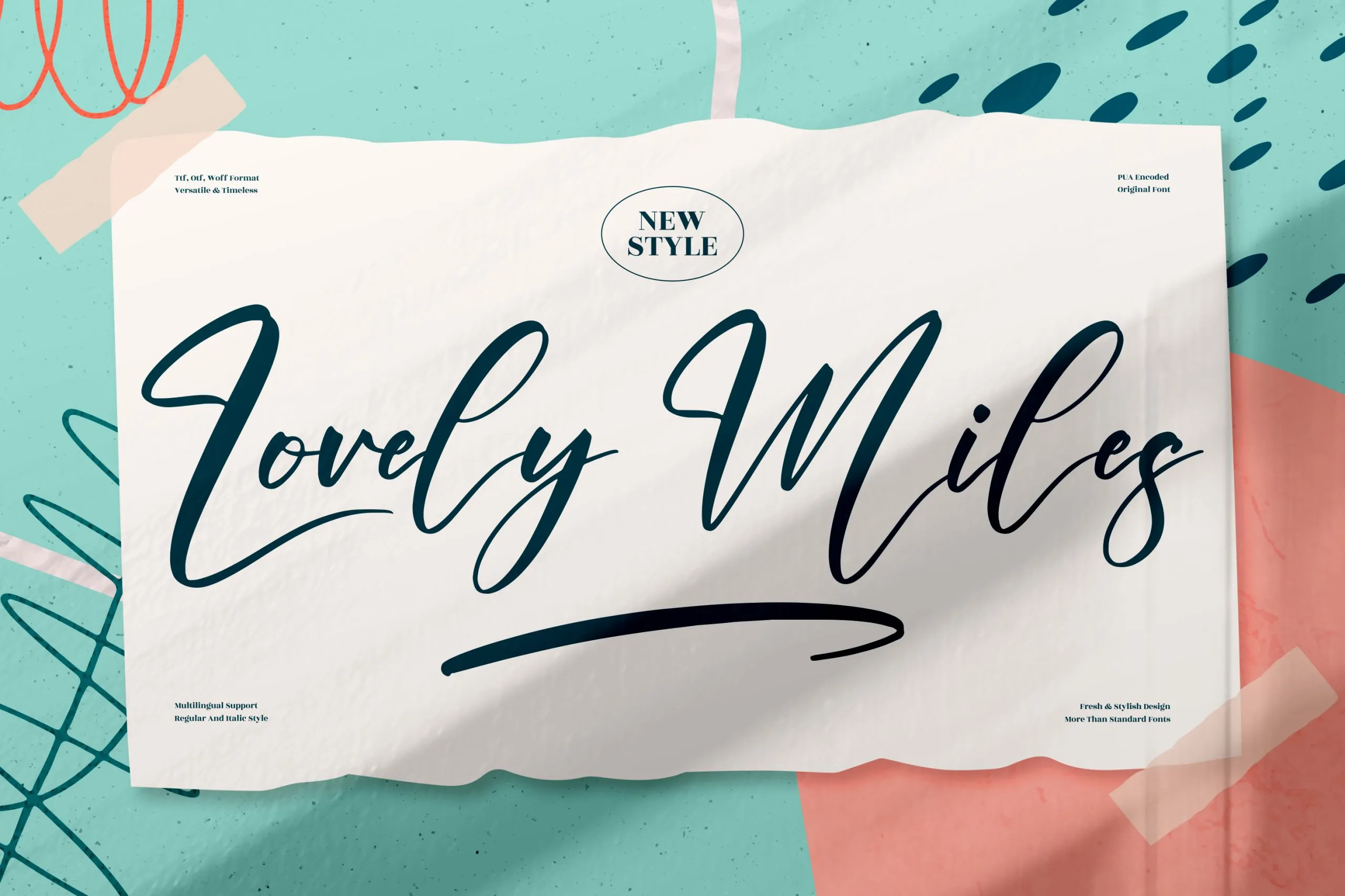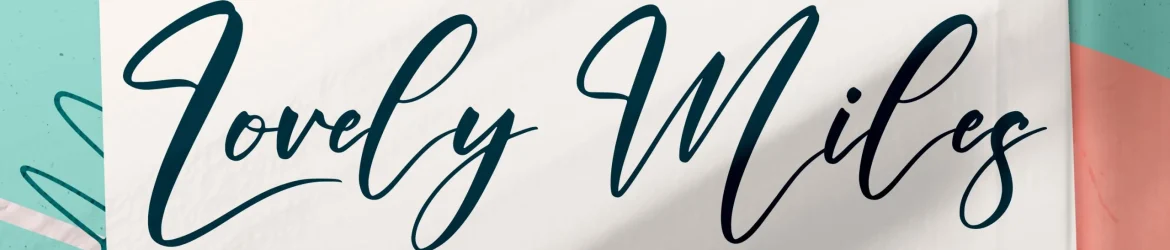
Lovely Miles Font – Download Grátis
Esta é uma fonte de calligrafia romântica perfeita para projetos variados. Adaptable a qualquer projeto que precise de uma pitada de bela script, esta fonte foi criada com amor e cuidado por perspectype, designer talentoso. Suas aplicações incluem logotipos, projetos de marca, designs de móveis de casa, embalagens de produtos, xícaras, citações, panfletos, sacolas de shopping, camisas, capas de livros, cartões de nome, cartões de convite, cartões de agradecimento, etiquetas, fotografia e até mesmo marcas de água. Se você está procurando por uma fonte que ofereça aquela pitada especial de beleza e sofisticação para seus trabalhos, esta é sua fonte perfeita. Perfecta para tudo que seja loooove!